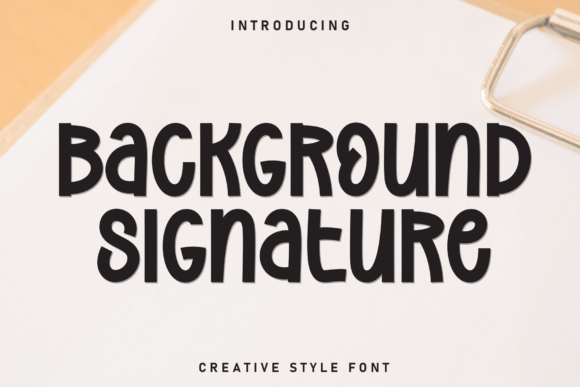
Background Signature
適切なデザイン要素を見つけるのは難しい場合がありますが、Background Signatureは作品を即座に引き立てる優れたコレクションを提供します。
POD(オンデマンド印刷)製品、結婚式の招待状、またはソーシャルメディアのグラフィックを作成している場合でも、Background Signatureは理想的です。